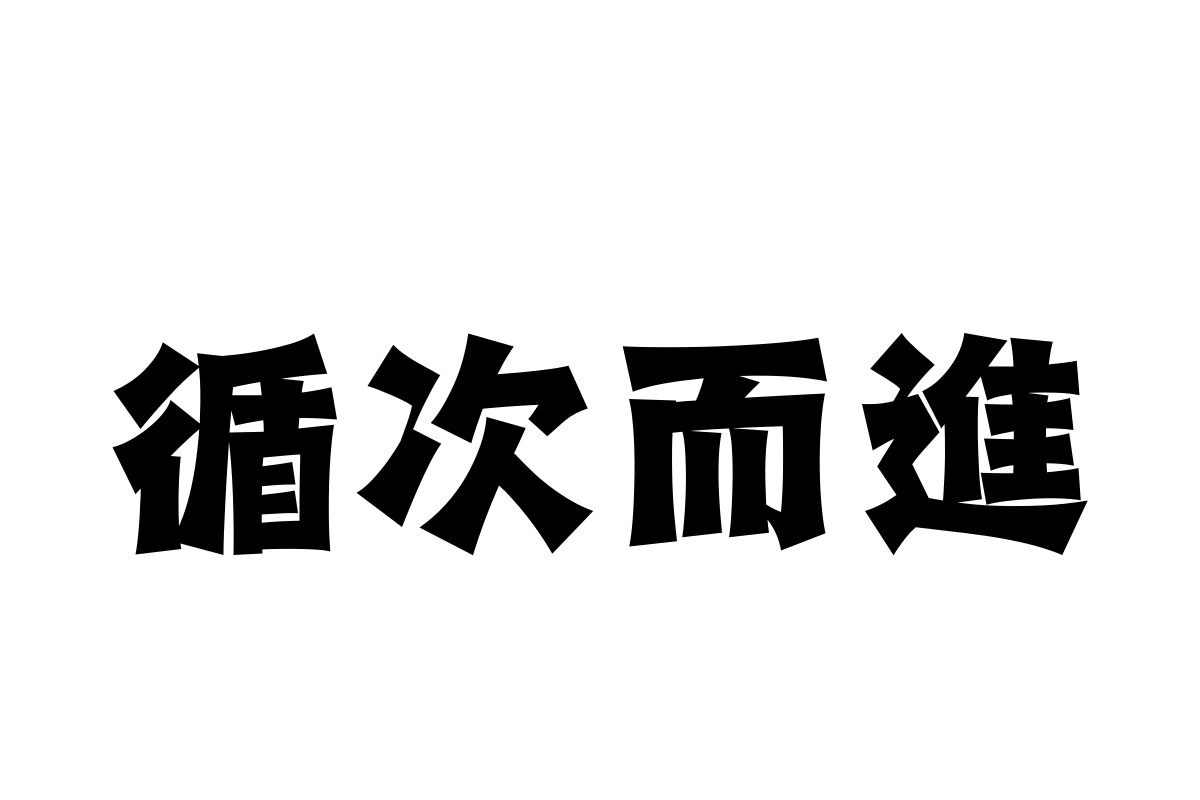
汉仪永字小喇叭繁体字体是一套专为中文排版设计的无衬线字体,由汉仪公司开发。该字体以其简洁、现代的设计风格而受到许多设计师和出版业的喜爱。
特点:
1. 无衬线设计:汉仪永字小喇叭繁体字体采用了无衬线的设计,这种设计使得文字看起来更加清晰、易读。
2. 多种字重:该字体提供了多种字重,包括常规、粗体、斜体等,以满足不同场景的需求。
4. 可定制性:虽然汉仪永字小喇叭繁体字体本身具有多种字重,但用户还可以通过调整字重来达到特定的效果,如增加或减少粗细变化等。
5. 适用于多种场景:无论是用于书籍、报纸、杂志还是网页设计,汉仪永字小喇叭繁体字体都能提供良好的视觉效果。
总的来说,汉仪永字小喇叭繁体字体是一款功能强大、易于使用的无衬线字体,适合各种中文排版需求。